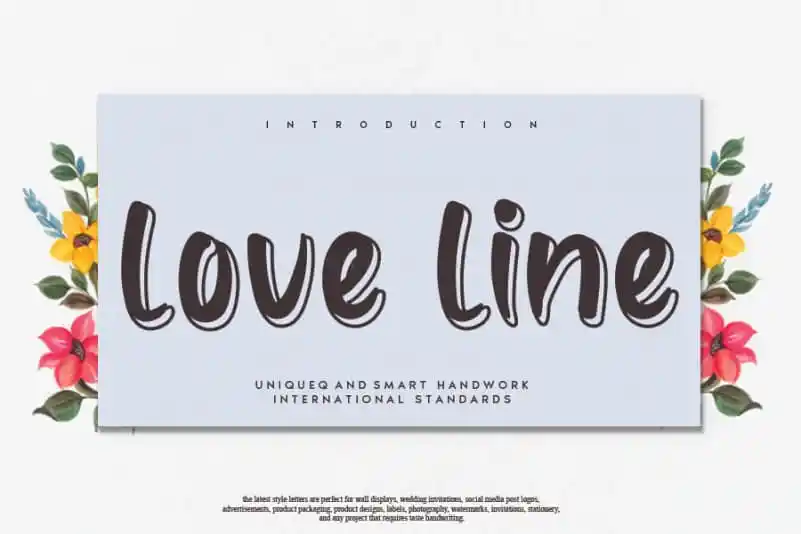
love line Display Font – Download Grátis
A ‘love line Display Font’ é uma elegante e acolhedora fórmula escrita a mão. Seu estilo natural e único permite que ela se adapte à vasta gama de projetos, limitada apenas pela imaginação do criador. Esta fonte pode transformar qualquer design em um trabalho de arte, fazendo dele ainda mais vívido e emocionalmente envolvente. Tornando-se a escolha perfeita para criar mensagens emotivas ou estilos simples, ela é ideal tanto para aplicações digitais quanto para impressão física. Não há limites à sua beleza, apenas suas próprias ideias criativas. Com certeza, ‘love line Display Font’ será uma fonte valiosa em qualquer coleção de recursos gráficos.